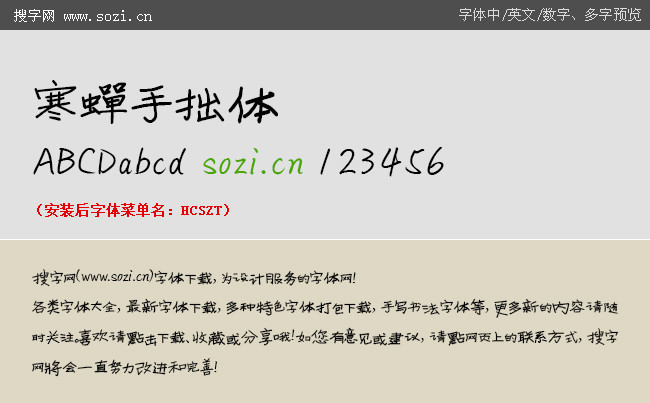
寒蟬手拙體
搜字網(wǎng)給大家提供一款寒蟬手拙體中文字體下載,寒蟬手拙體是站酷設(shè)計師 siue 創(chuàng)作的字體,主要精髓為發(fā)掘手寫字體的手拙之美,字體給人一種逼真手寫的視覺體驗。雖應(yīng)用范圍有限,但有其不可替代和獨特的價值。以創(chuàng)造的筆意和結(jié)構(gòu)完成,形成風(fēng)格獨特的一套小眾字體。該字體免費授權(quán)全社會使用(包括商用)。